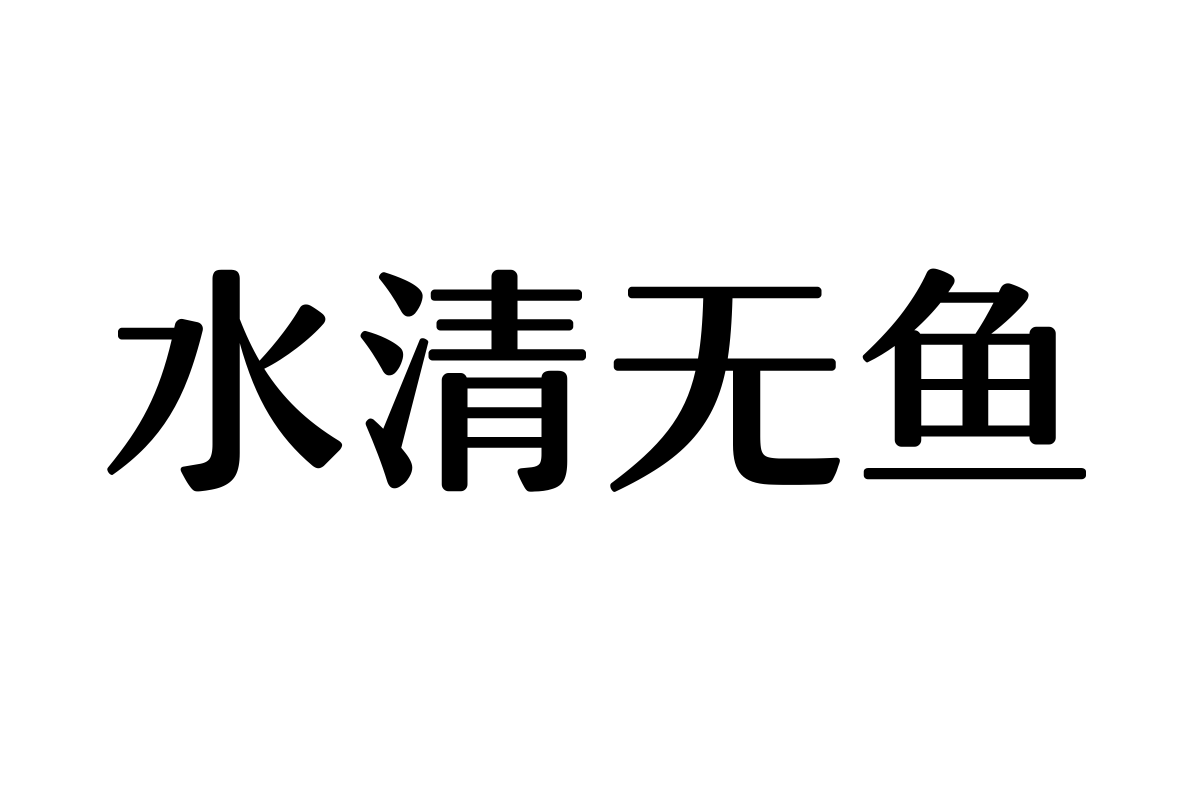
汉仪润圆-65是一款具有现代感的中文字体,其特点是字形圆润饱满,线条流畅自然。这款字体适用于各种需要表现柔和、舒适氛围的设计作品,如广告、海报、包装等。同时,由于其圆润的字形设计,也适合用于一些需要强调亲和力和亲切感的场合,如儿童用品、家居用品等。总的来说,汉仪润圆-65是一款非常实用且美观的字体,能够满足广大设计师的需求。